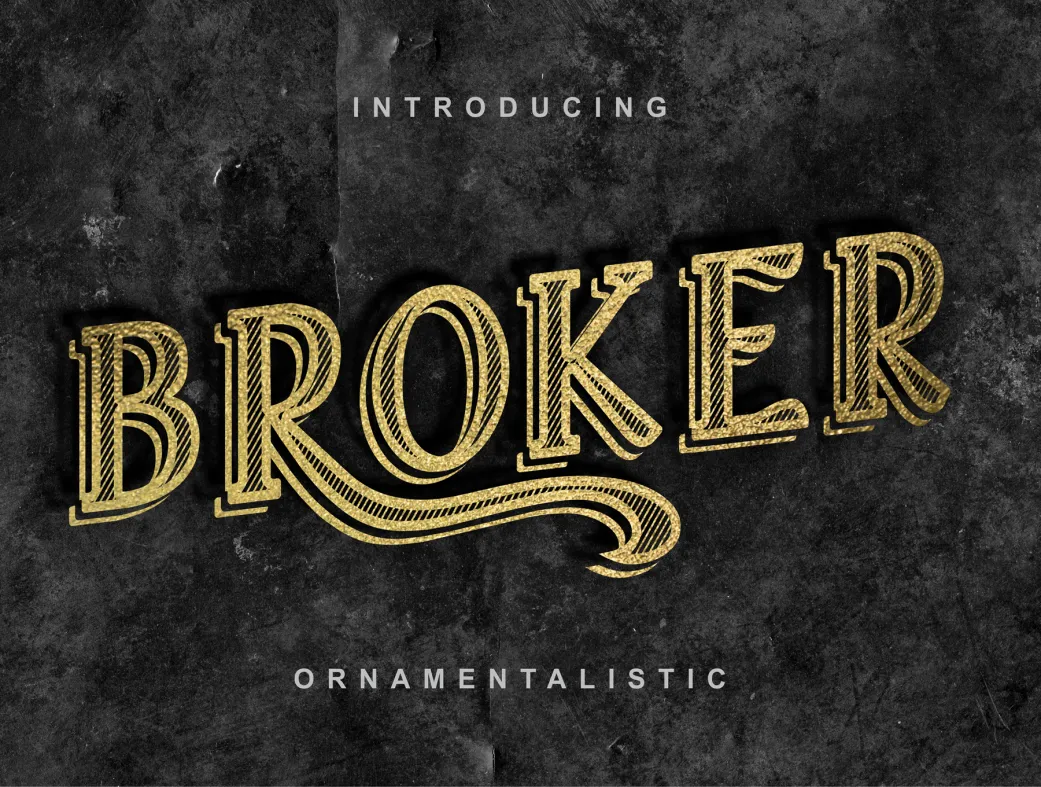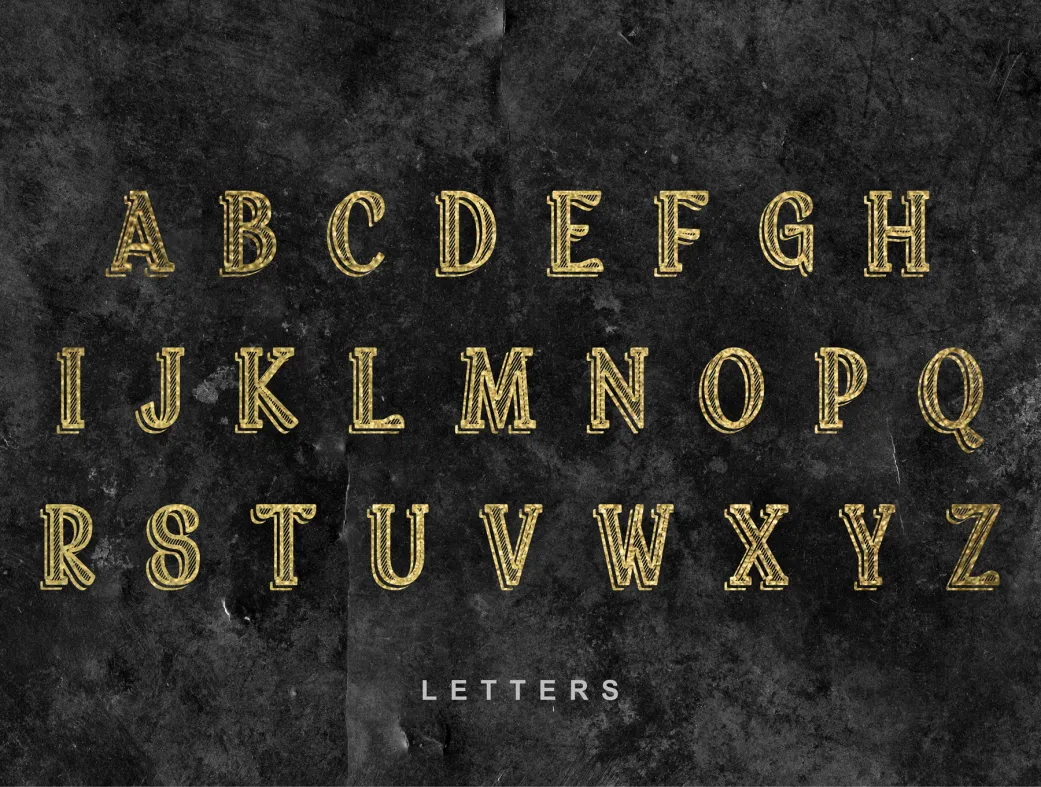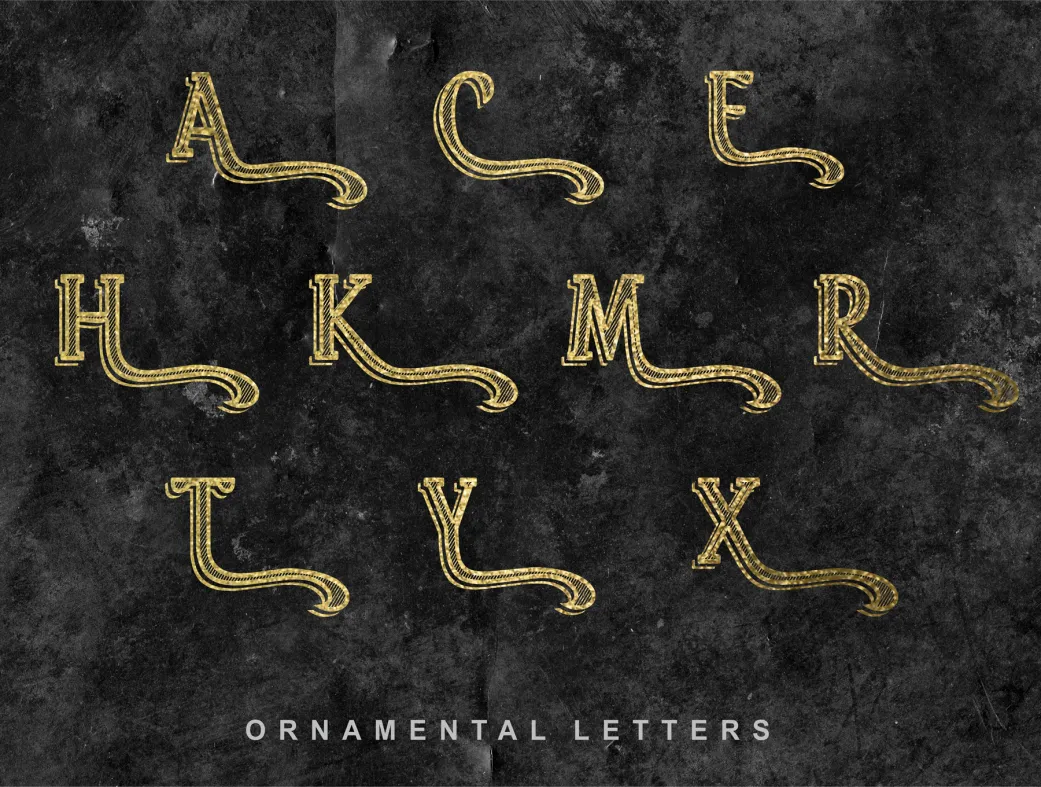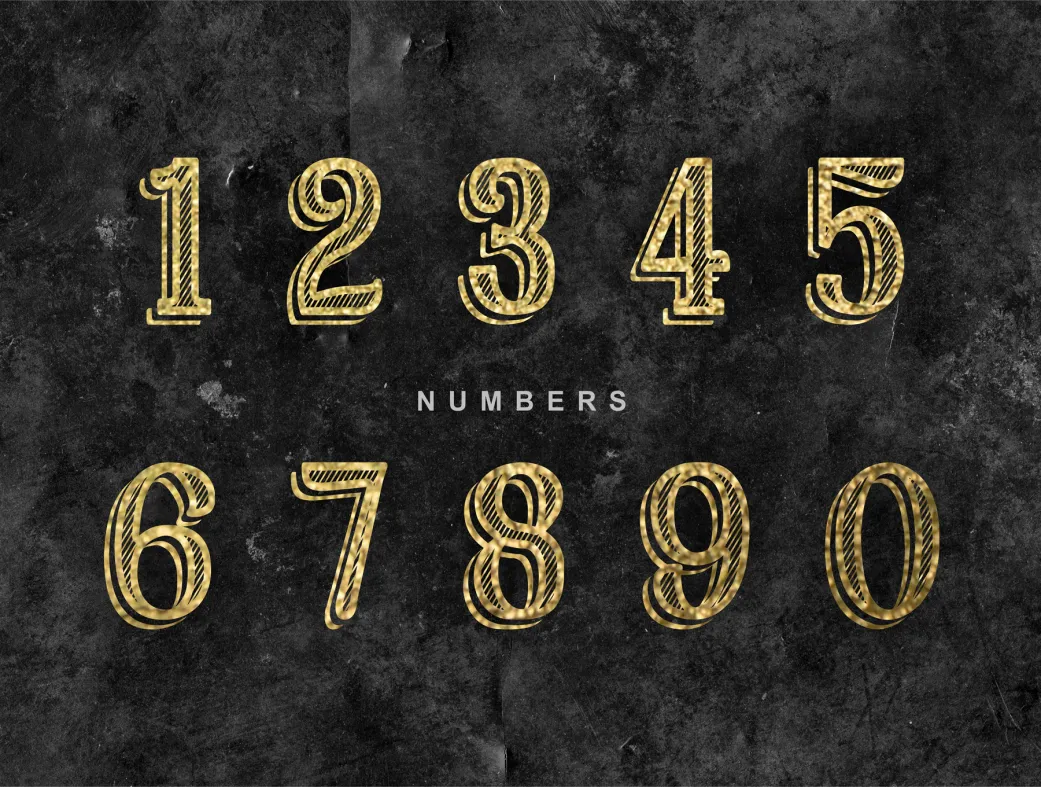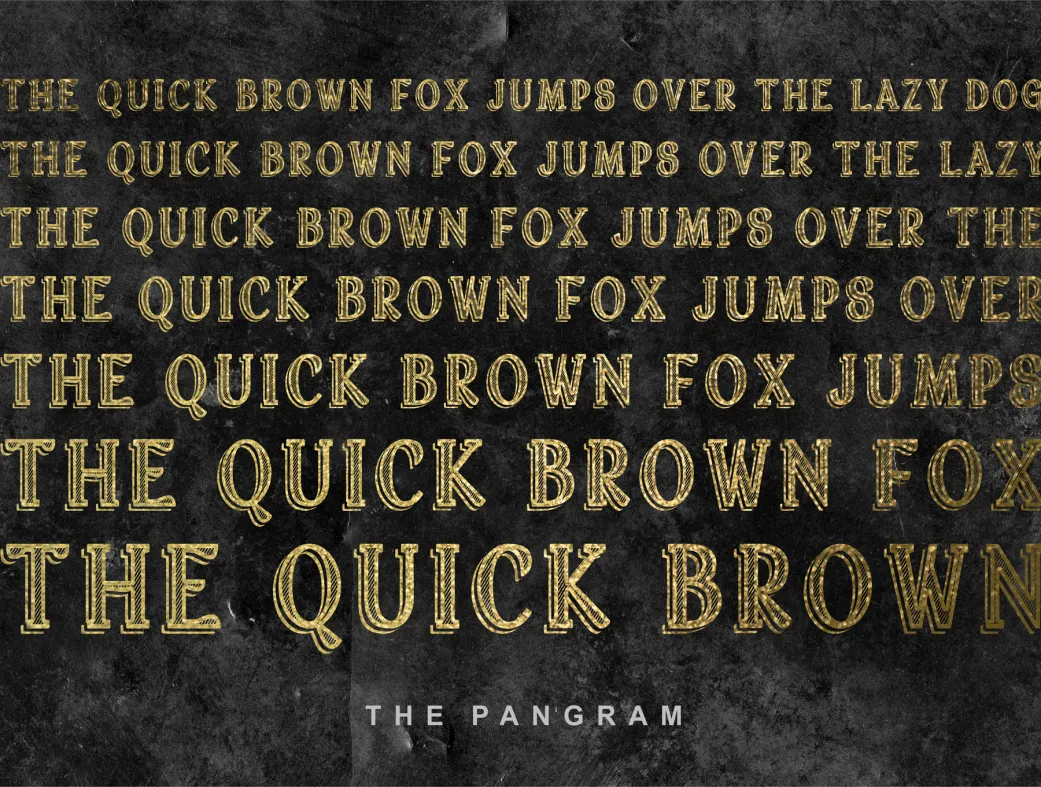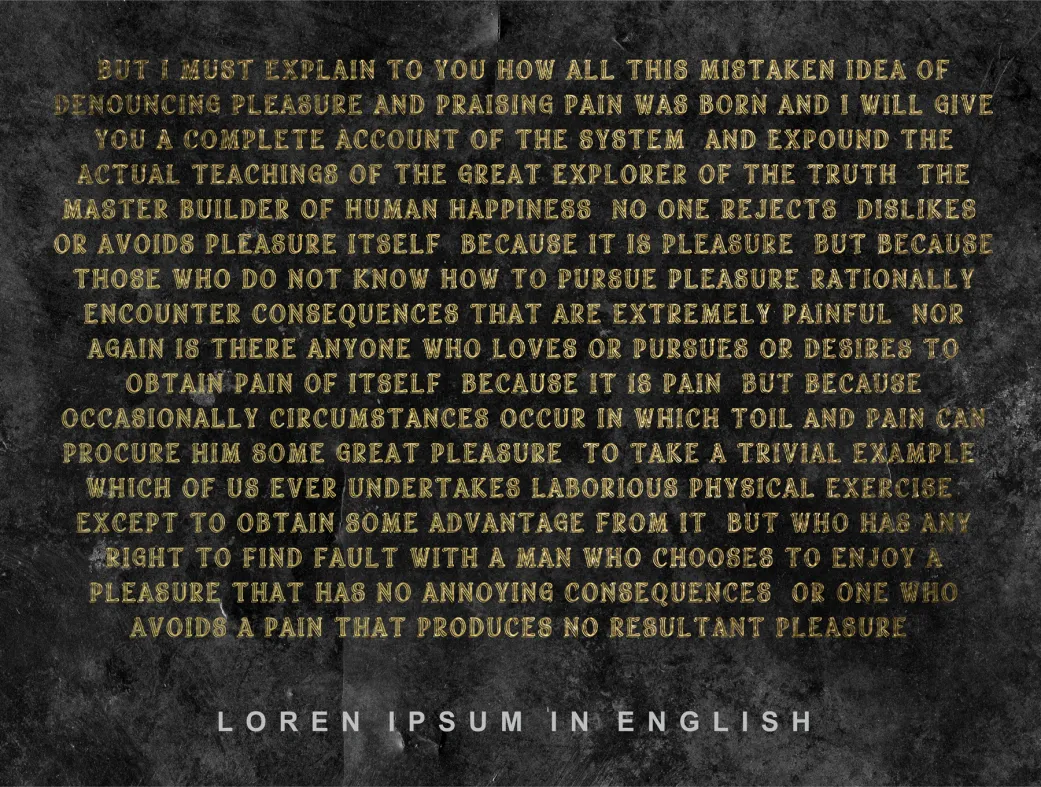
فونت بروکر | Broker
فونت بروکر، طراحی خشن و حرفه‌ای برای جذابیت بصری شما! مناسب برای پروژه‌های تجاری و تبلیغاتی.
Broker
فونت بروکر یک فونت قوی و مختصر با پایه‌های محکم و لبه‌های تیز است. این فونت خشن برای طراحی‌های خاصی مانند جلد کتاب‌ها، تیترهای تبلیغاتی، بنرهای وب‌سایت و نوشتار لوگوها مناسب است. الهام‌گرفته از دنیای کسب و کار و مالی، فونت بروکر در بسیاری از طراحی‌ها قابل استفاده و انعطاف‌پذیر است.
فونت بروکر با طراحی منحصر به فرد خود، به راحتی می‌تواند توجه مخاطبان را جلب کند و به کارهای شما ظاهری حرفه‌ای و مدرن ببخشد. این فونت علاوه بر حروف اصلی، دارای حروف اضافی زینتی نیز است که می‌تواند به طراحی‌های شما عمق و جذابیت بیشتری ببخشد. حروف زینتی از طریق منوی نمادها در هر برنامه نرم‌افزاری قابل دستیابی هستند، که این امکان را به طراحان می‌دهد تا خلاقیت بیشتری در طراحی‌های خود به کار ببرند.
فونت بروکر کاربردهای متنوعی دارد، از جمله طراحی جلد کتاب‌ها، تیترهای داخل فصول، طراحی پوسترها یا کارت‌های پستال، دکوراسیون‌های جشن و کارت‌های تبریک، نامه‌های دعوت و پاکت‌های تجاری. این فونت به دلیل استحکام و طراحی زیبا، انتخابی مناسب برای هر نوع پروژه‌ای است که نیاز به جذابیت بصری دارد.
برای کاربران حرفه‌ای و مبتدی، فونت بروکر می‌تواند در طراحی‌های مختلفی مورد استفاده قرار گیرد. از جمله استفاده در طراحی جلد کتاب، تیترها، پوسترها و حتی کارت‌های دعوت. برای بهترین نتیجه، پیشنهاد می‌شود که با ترکیب فونت بروکر با رنگ‌ها و طرح‌های متناسب، جذابیت بیشتری به آثار خود ببخشید.
3. آیا این فونت مناسب طراحی‌های تجاری است؟
بله، فونت بروکر به طور خاص برای طراحی‌های مرتبط با کسب و کار و مالی طراحی شده و به خوبی با این نوع پروژه‌ها سازگار است.
5. آیا این فونت می‌تواند در طراحی وب‌سایت‌ها استفاده شود؟
بله، این فونت مناسب برای طراحی بنرهای وب‌سایت و متن‌های تبلیغاتی است.